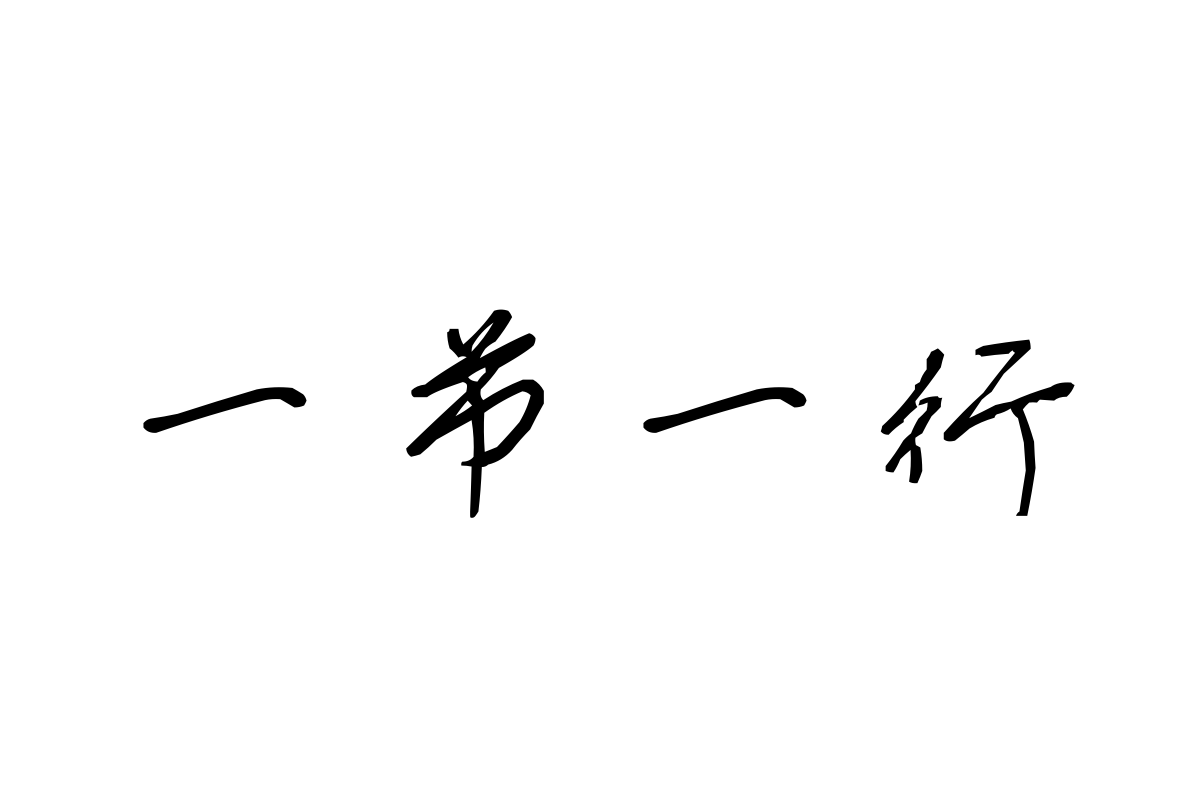
三极吴峰行楷字体,又称吴峰行楷体,是一种具有独特风格和特点的书法字体。这种字体以其流畅、优美的线条和独特的结构而闻名,给人一种优雅而庄重的感觉。
三极吴峰行楷字体的主要特点是其笔画的粗细变化和结构的对称性。在书写时,每个字的笔画都呈现出一种自然的曲线,使得整个字体看起来既流畅又富有韵律感。同时,这种字体的结构也呈现出一种对称性,使得整体看起来更加和谐统一。
此外,三极吴峰行楷字体还具有很高的辨识度。它的笔画粗细变化丰富,既有粗犷豪放的一面,也有细腻柔美的一面,这使得每一个字都显得独特而富有个性。同时,由于其独特的结构,使得整个字体看起来既庄重又不失灵动,给人一种优雅而庄重的感觉。
总的来说,三极吴峰行楷字体是一种极具艺术价值和观赏性的书法字体,它以其流畅、优美的线条和独特的结构,展现了汉字的独特魅力和文化内涵。